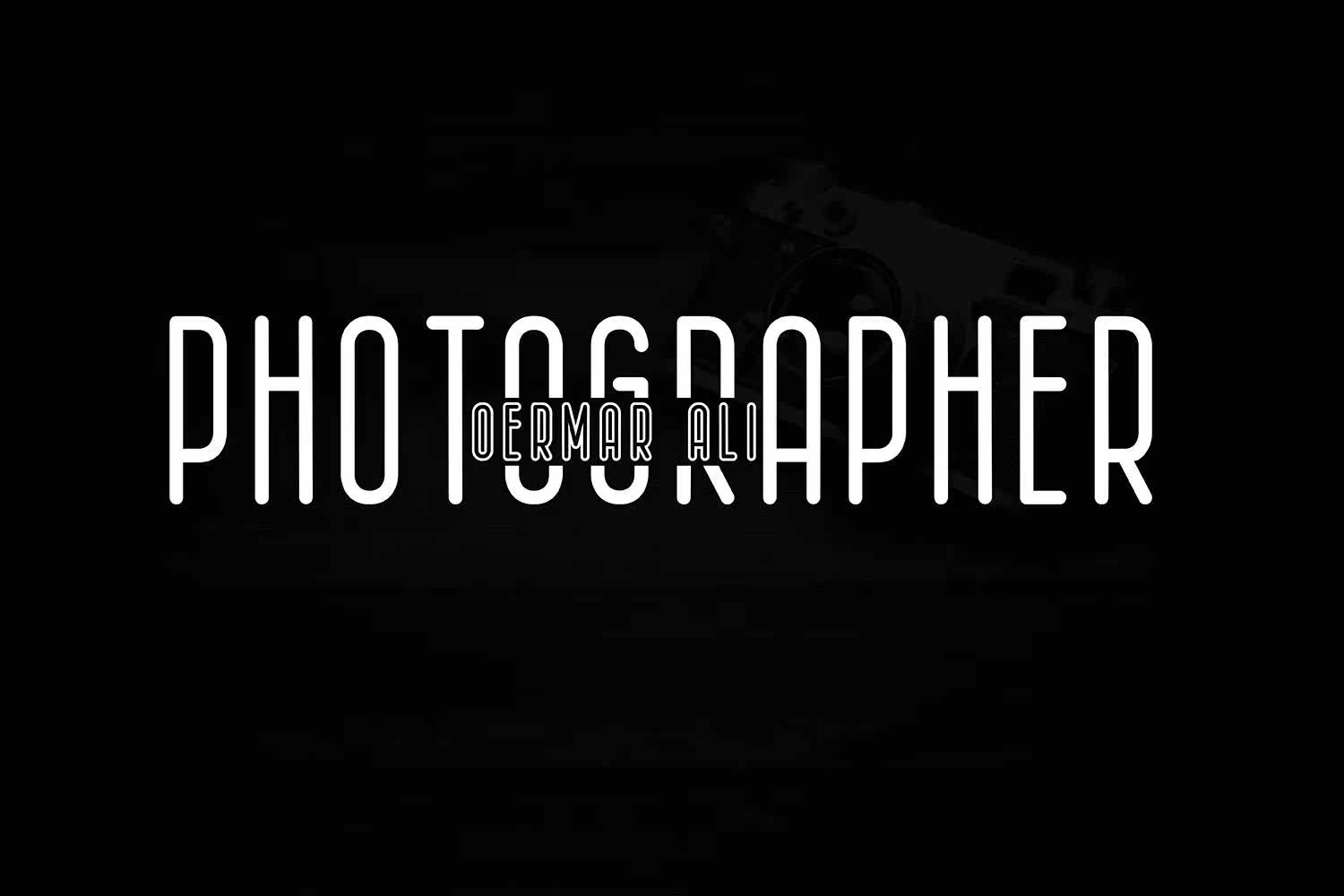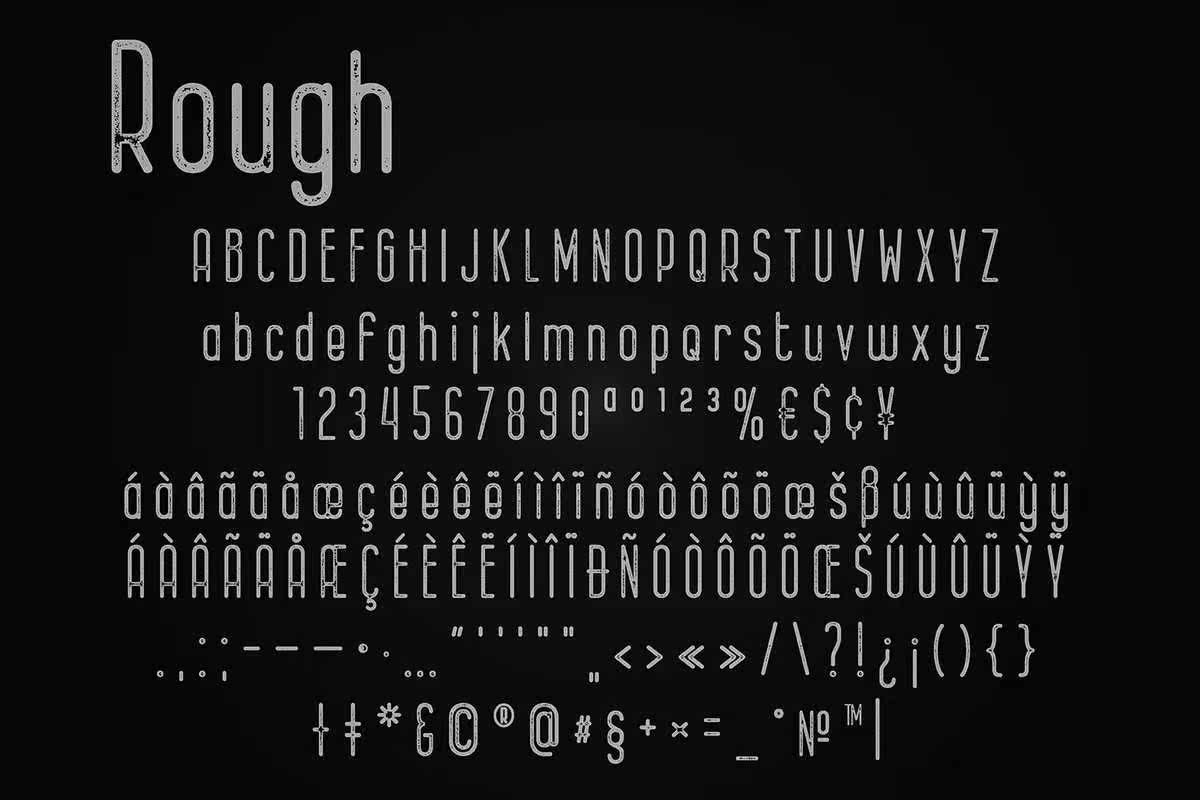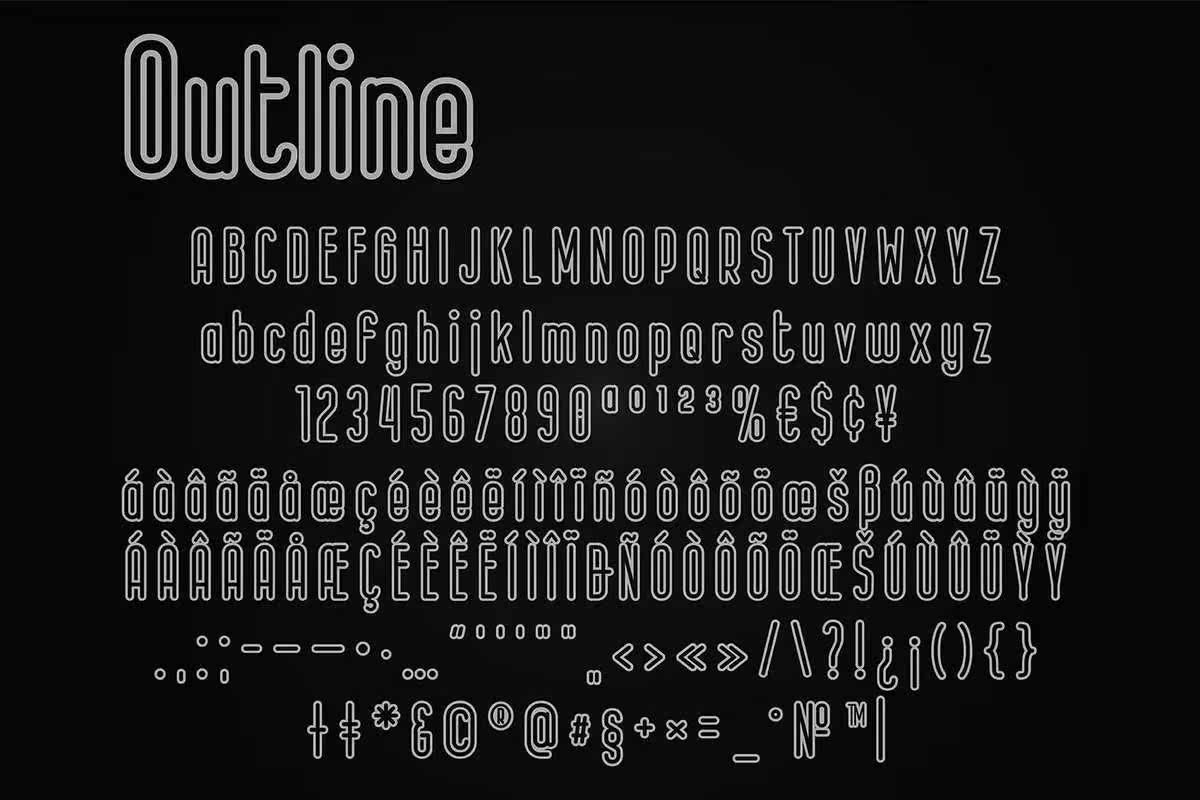
Bernound是三种不同颜色的Namazing字体。净重通过角和细长的形状呈现相同的最小压力。安全带的外线重量显示在自己的屏幕上,并且重量足够大,但不带有质感,和GrungeLook。所有重量都可以完美组合,这使我们有机会仅通过此下载创建无休止的液体设计。Bernounds是三种重量的Namazing字体。清洁重量可以通过角进行旋转,形状也可以在当前相同的最小压力下进行。Outlined Weights Safancy自己显示,并且重量足够大,质朴、粗糙的外观。所有重量都可以完美结合,从而使我们有机会仅通过此下载创建无限制的智能设计。